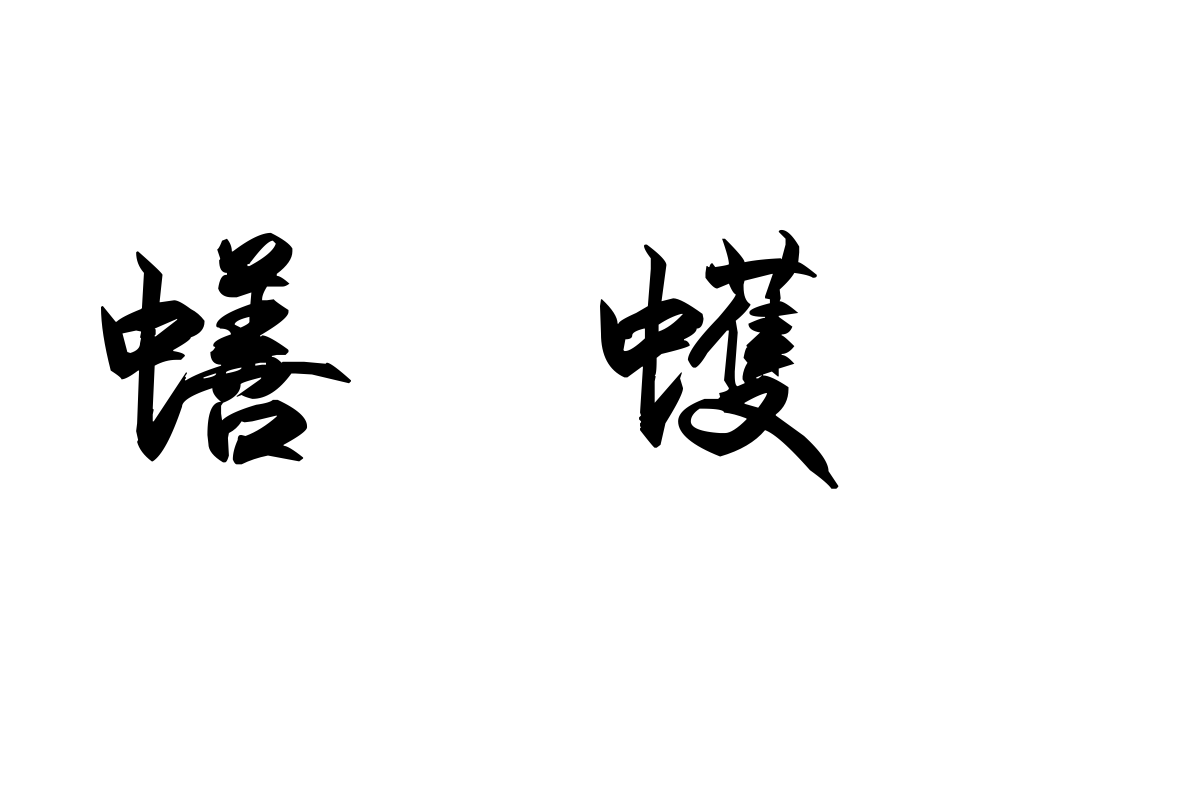
米开飘逸行楷字体是一款现代的、具有艺术风格的字体,它结合了行书和楷书的特点,创造出了一种既优雅又动感的字体。这种字体的特点是笔画流畅,结构简洁,线条粗细变化丰富,给人一种轻松、自然的感觉。
米开飘逸行楷字体的特点如下:
1. 笔画流畅:这种字体的笔画连接自然,没有过多的断笔和连笔,使得整体看起来更加清晰、易读。
2. 结构简洁:虽然是一种艺术字体,但米开飘逸行楷字体的结构依然保持了一定的规律性,使得整体看起来更加整洁、有序。
3. 线条粗细变化丰富:这种字体的线条粗细变化丰富,既有粗犷的线条,也有细腻的线条,使得整体看起来更加生动、有趣。
4. 易于识别:由于其独特的风格,米开飘逸行楷字体在视觉上具有很强的辨识度,使得人们在阅读时能够迅速识别出文字。
5. 适用于多种场景:无论是用于书籍、杂志、广告还是网页设计,米开飘逸行楷字体都能很好地融入其中,展现出其独特的魅力。
米开飘逸行楷